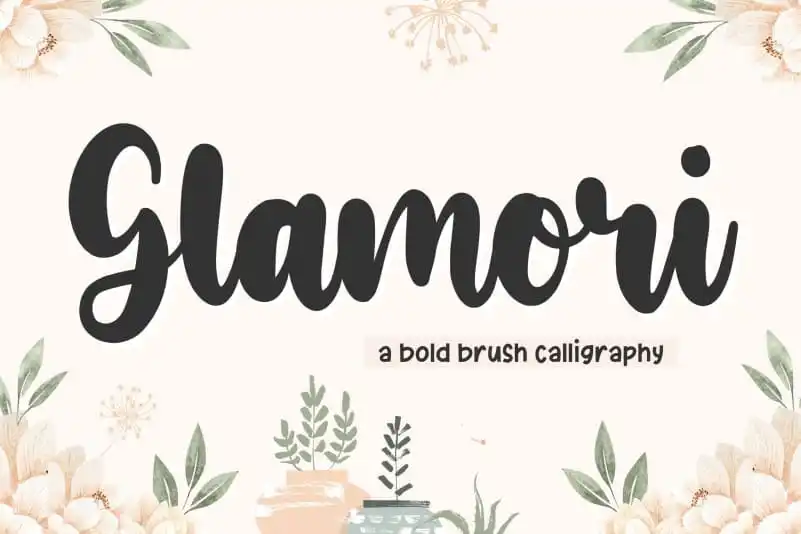
Glamori Bold Script Font – Fonte Grátis
Glamori Bold Script Font
A fonte Glamori Bold Script é uma escolha ideal para qualquer projeto que necessite de personalidade e elegância. Seja para embalagens de produtos, criação de marca, revistas, redes sociais, casamentos ou mesmo simplesmente expressar mensagens sobre fundo, a Glamori Bold Script oferece um toque sofisticado e envolvente. Suave mas forte, esta fonte traz uma cadência que transmite seriedade ao mesmo tempo em que exibe criatividade. Perfeita para destacar texto em páginas de revistas ou redes sociais, essa font pode transformar qualquer mensagem em um ponto focal. Suas características fortes permitem usá-la tanto no topo da página como na parte inferior, garantindo sempre o foco do leitor. A Glamori Bold Script é a escolha certa para quem deseja dar uma batida única e profissional aos projetos de marca ou publicidade. Ideal para criar um impacto visual imediato em produtos de consumo, sites web, banners de marketing ou até mesmo no design de cartões de visitas. Com sua versatilidade e estilo único, a Glamori Bold Script atende às necessidades de qualquer projeto que busque expressar uma mensagem através do formato e da forma. Seja você um designer gráfico experimentando novos estilos, ou simplesmente alguém buscando adicionar um toque especial ao seu design, essa fonte oferece o poder necessário para fazer isso acontecer.